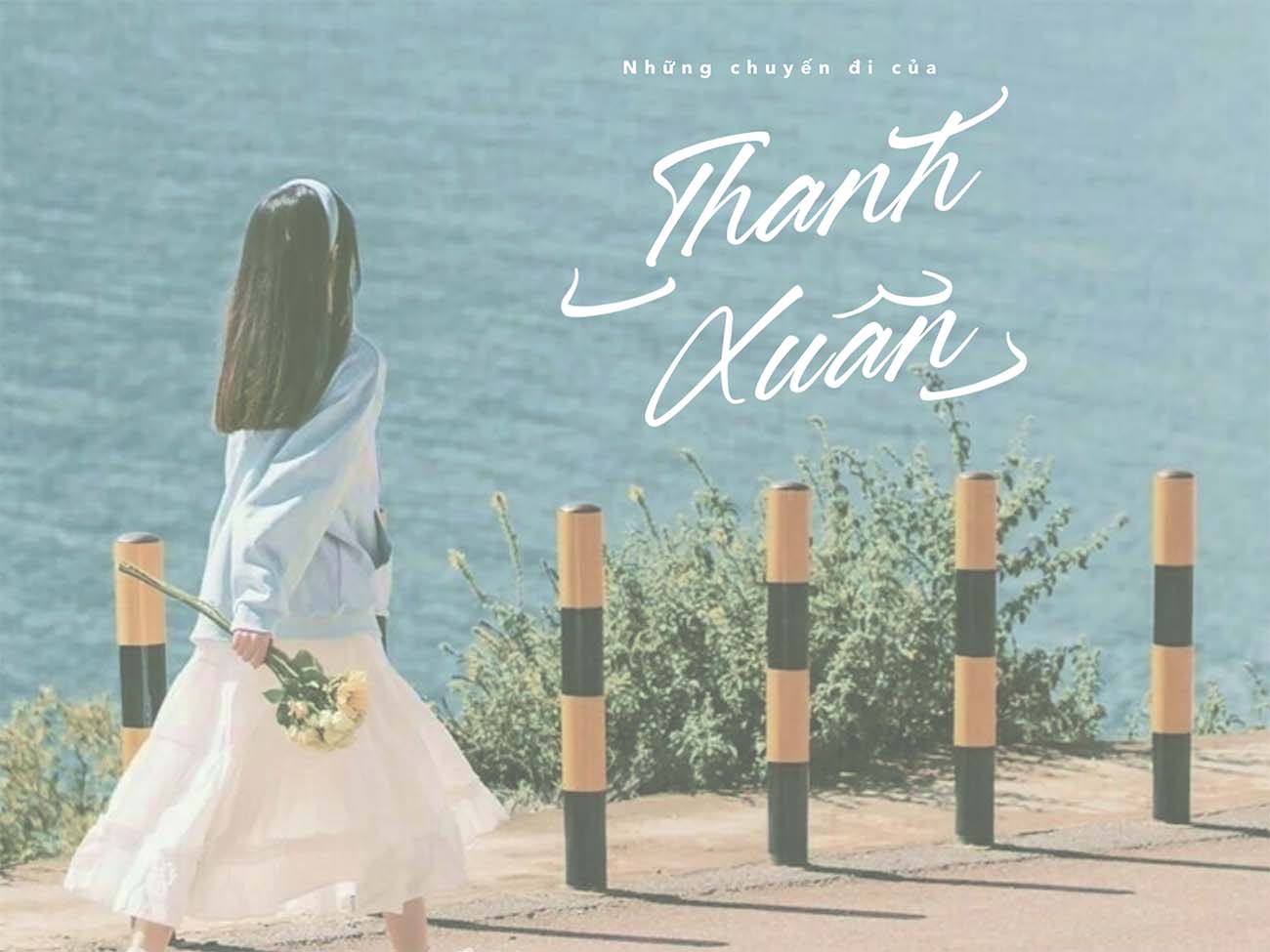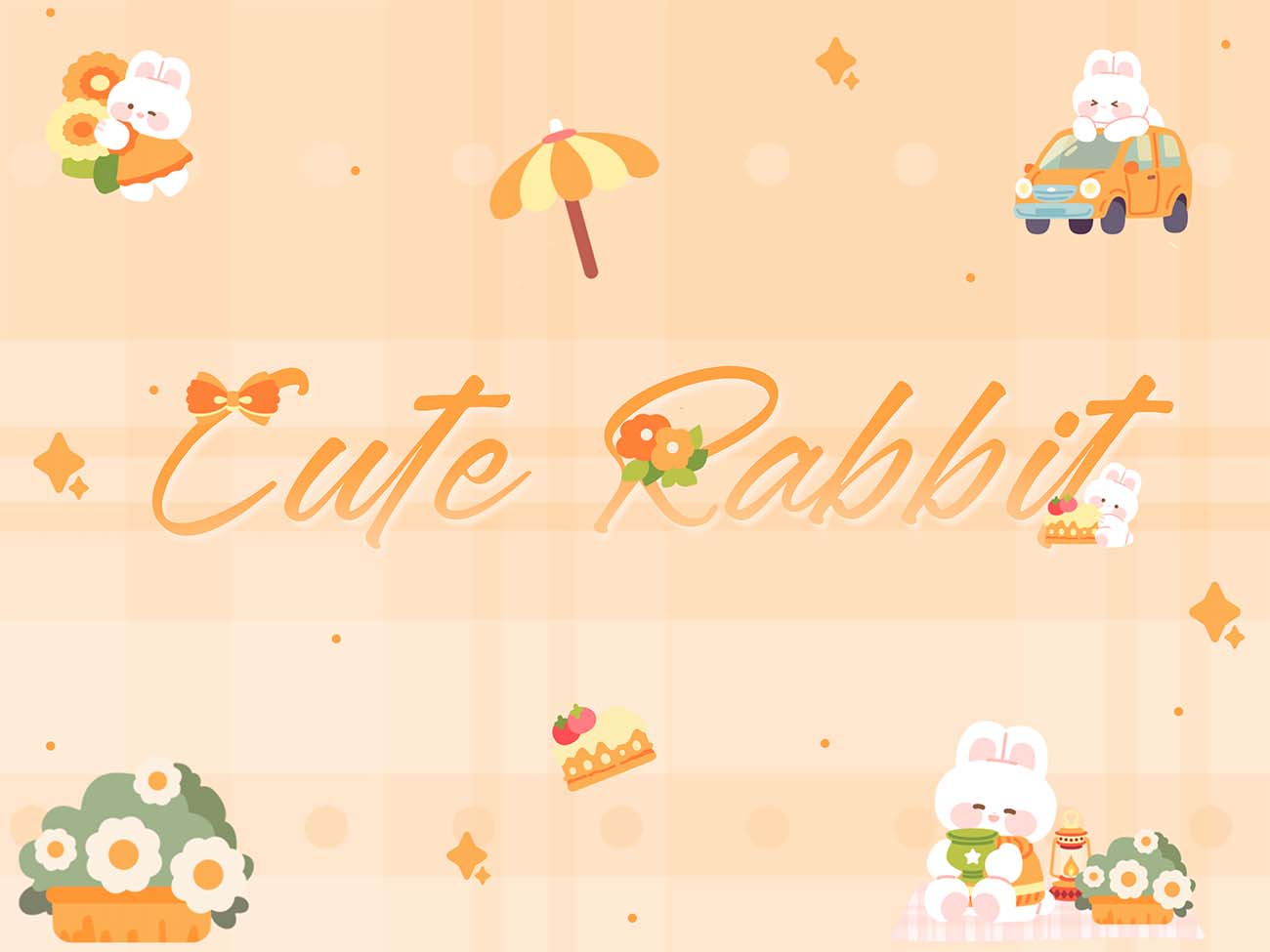
Phông chữ ký TH Jonathan Stattera Việt hóa dành cho thiết kế thiệp cưới
Trong thế giới Typography hiện đại, việc tìm kiếm một phông chữ vừa mang tính cá nhân hóa cao, vừa giữ được sự sang trọng là điều mà mọi Designer đều hướng tới. Hôm nay, chúng tôi xin giới thiệu đến cộng đồng thiết kế bộ phông chữ TH Jonathan Stattera, một tuyệt phẩm được Việt hóa bởi Team TH từ bản gốc của tác giả Letterena.
Ứng dụng hoàn hảo cho mùa cưới
Với phong cách lãng mạn đặc trưng, TH Jonathan Stattera sinh ra là để dành cho các thiết kế liên quan đến tình yêu và hạnh phúc. Đây chắc chắn là font thiệp cưới mà các nhà thiết kế không thể bỏ qua trong bộ sưu tập của mình.
Sự sang trọng của nó giúp nâng tầm giá trị của các ấn phẩm như thiệp mời, menu tiệc, bảng tên cô dâu chú rể hay các video phóng sự cưới. Khi sử dụng làm font đám cưới, TH Jonathan Stattera mang lại cảm giác thân mật, ấm cúng nhưng không kém phần đẳng cấp, giúp ngày trọng đại trở nên đáng nhớ hơn qua từng con chữ.
Vẻ đẹp tinh tế của Jonathan Stattera
Jonathan Stattera (bản gốc) là một phông chữ dạng chữ ký (Signature Script) mang phong cách hiện đại và phóng khoáng. Điểm thu hút nhất của bộ font này chính là sự kết hợp hài hòa giữa các đường cong mềm mại và tính tự nhiên như chữ viết tay thật.
Đây là lựa chọn hoàn hảo cho những ai đang tìm kiếm một font chữ nét mảnh đầy tinh tế. Các ký tự được thiết kế với độ dày vừa phải, tạo cảm giác nhẹ nhàng, bay bổng nhưng vẫn đảm bảo tính dễ đọc. Sự liền mạch trong các nét nối giúp tổng thể văn bản trở nên mượt mà, rất thích hợp cho các tiêu đề cần sự trang nhã.
Bản Việt hóa từ Team TH
Mặc dù bản gốc Jonathan Stattera đã rất đẹp, nhưng việc thiếu các ký tự tiếng Việt có dấu thường gây khó khăn cho Designer trong nước. Hiểu được điều đó, Team TH đã thực hiện Việt hóa trọn vẹn bộ phông chữ này với tên gọi TH Jonathan Stattera.
Bản Việt hóa không chỉ bổ sung đầy đủ dấu tiếng Việt chuẩn mà còn được tinh chỉnh lại kerning (khoảng cách giữa các chữ) để phù hợp hơn với ngữ pháp và thẩm mỹ của người Việt. Điều này giúp các bạn thoải mái sáng tạo nội dung mà không lo bị lỗi font hay dấu bị lệch, đảm bảo sự chuyên nghiệp tuyệt đối cho sản phẩm cuối cùng.
Lời kết
TH Jonathan Stattera là một công cụ đắc lực cho các dự án Branding, nhiếp ảnh, chữ ký và đặc biệt là lĩnh vực cưới hỏi. Hy vọng bộ phông chữ này sẽ mang lại nguồn cảm hứng mới mẻ cho các thiết kế sắp tới của bạn.